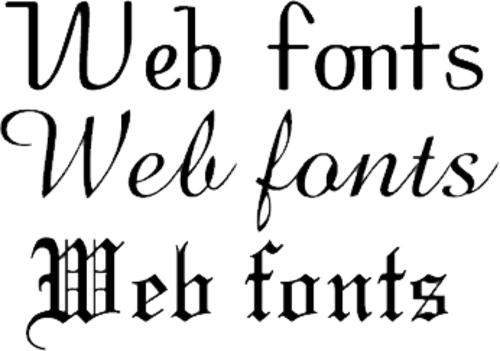
ウェブ タイポグラフィは、一般的なタイポグラフィと同様に、ページのデザイン、つまりレイアウトと書体の選択です。従来の印刷ベースのタイポグラフィ (ページは一度タイプセットされると固定されます) とは異なり、ワールド ワイド ウェブでの表示を目的としたページには追加の技術的課題があり、プレゼンテーションを動的に変更できるため、追加の機会があります。初期のウェブ ページ デザインは、技術的な制限により非常に単純でしたが、最新のデザインでは、カスケーディング スタイル シート(CSS)、JavaScript、およびその他のテクニックを使用して、タイポグラファーとクライアントのビジョンを実現します。
HTMLが最初に作成されたとき、書体とスタイルは各Web ブラウザの設定によってのみ制御されていました。Netscape が1995 年に 要素を導入しfont、その後 HTML 3.2 仕様で標準化されるまで、個々の Web ページでフォントの表示を制御するメカニズムはありませんでした。ただし、要素で指定されたコンピュータ フォントはfont、ユーザーのコンピュータにインストールされているか、ブラウザのデフォルトのサンセリフフォントや等幅フォントなどのフォールバックフォントが使用される必要がありました。最初の CSS 仕様は 1996 年に公開され、同じ機能を提供しました。
CSS2仕様は1998年にリリースされ、フォントのマッチング、合成、ダウンロードを追加することでフォント選択プロセスの改善を試みました。これらの技術はあまり使用されなかったので、CSS2.1仕様では削除されました。しかし、Internet Explorerは1997年にリリースされたバージョン4.0でフォントダウンロード機能のサポートを追加しました。[1]フォントのダウンロードは後にCSS3フォントモジュールに含まれ、 Safari 3.1、Opera 10、Mozilla Firefox 3.5に実装されました。これにより、Webタイポグラフィへの関心が高まり、フォントダウンロードの使用も増加しました。
CSS1
最初のCSS仕様では、[2]著者は一連のプロパティを通じてフォントの特性を指定しました。
font-familyfont-stylefont-variantfont-weightfont-size
すべてのフォントは名前だけで識別されていました。上記のプロパティ以外に、デザイナーがフォントのスタイルを設定する方法はなく、クライアント システムに存在しないフォントを選択するメカニズムもありませんでした。
ウェブセーフフォント
Web セーフ フォントは、幅広いコンピュータシステムに存在することが合理的に期待できるコンピュータ フォントであり、Webコンテンツの作成者が、コンテンツが選択したフォントで表示される可能性を高めるために使用します。Web サイトの訪問者が指定されたフォントを持っていない場合、ブラウザは、作成者が指定したフォールバック フォントと汎用ファミリに基づいて類似の代替フォントを選択しようとするか、訪問者のオペレーティング システムで定義されている フォントの代替を使用します。
Microsoft の Web 向けコアフォント
すべての Web ユーザーが基本的なフォント セットを利用できるようにするために、Microsoft は1996 年にCore fonts for the Webイニシアチブを開始しました(2002 年に終了)。リリースされたフォントには、 Arial、Courier New、Times New Roman、Comic Sans、Impact、Georgia、Trebuchet、Webdings、Verdanaなどがあります。EULAでは、これらのフォントは自由に配布できるものの、使用権が一部制限されていました。これらのフォントは普及率が高いため、Web デザイナーにとって欠かせないものとなっています。ただし、ほとんどのLinux ディストリビューションには、これらのフォントがデフォルトで含まれていません。
CSS2は、フォント合成、フォントマッチングの改善、リモートフォントのダウンロード機能を追加することで、Web開発者が利用できるツールを増やそうとしました。[3]
CSS2フォントプロパティの一部はCSS2.1から削除され、後にCSS3に含まれました。[4] [5]
フォールバックフォント
CSS仕様では、複数のフォントをフォールバックフォントとしてリストすることができます。[6] CSSでは、font-familyプロパティは次のように使用するフォントフェイスのコンマ区切りのリストを受け入れます。
フォントファミリ: "Nimbus Sans L" 、Helvetica 、Arial 、sans-serif ;
最初に指定されたフォントが優先フォントです。このフォントが使用できない場合、Web ブラウザはリスト内の次のフォントの使用を試みます。指定されたフォントが見つからない場合、ブラウザはデフォルトのフォントを表示します。ブラウザが指定されたフォントに存在しない文字を表示しようとした場合も、同じプロセスが文字ごとに実行されます。
汎用フォントファミリー
ウェブデザイナーがウェブページ上のフォントの外観をある程度制御できるように、指定されたフォントが利用できない場合でも、CSS 仕様ではいくつかの汎用フォント ファミリの使用が許可されています。これらのファミリは、フォントを一般的な外観に基づいていくつかのカテゴリに分割するように設計されています。これらは通常、作成者が指定したフォントが利用できない場合の最後の手段として、一連のフォールバック フォントの最後に指定されます。数年間、汎用ファミリは 5 つありました。[6]
- 文字に装飾的なマークやセリフがないフォント。これらのフォントは画面上で読みやすいとよく考えられています。[7]
- 文字に装飾的なマークやセリフがあるフォント。これらのフォントは伝統的に印刷書籍で使用されています。
- すべての文字の幅が等しいフォント。
- 筆記体に似たフォント。これらのフォントは装飾的な外観を持ちますが、小さいサイズでは読みにくいため、通常は控えめに使用されます。
ファンタジー
- 記号やその他の装飾プロパティを含みながらも、指定された文字を表すフォント。
CSS フォントのワーキングドラフト 4 (ブラウザのサポートが少ない)
2024年2月現在[アップデート]、W3CのCSSワーキンググループは、システムがタグを使用してデフォルトのフォントを指定することを提案しています。[8]同日現在、これらはまだ広くサポートされていません。[9]ui
- システムUI
- 特定のシステムのデフォルト フォント: このオプションの目的は、Web コンテンツをネイティブ OS のルック アンド フィールと統合できるようにすることです。
- uiセリフ
- 特定のシステムにおけるセリフ体のデフォルトフォント
- サンセリフ
- 特定のシステム上のサンセリフ スタイルのデフォルト フォント
- ui-モノスペース
- 特定のシステムにおける等幅フォントのデフォルトフォント
- ui-丸め
- 丸みを帯びたスタイルの特定のシステムのデフォルトフォント
- 絵文字
- 絵文字を使ったフォント
- 数学
- 複雑な数式や表現用のフォント。
- Fangsong (中国語:仿宋体)
- セリフ体の宋体と草書体の楷書体の中間に位置する中国語の書体。このスタイルは、政府文書によく使用されます。
ウェブフォント
歴史
リモートフォントを参照して自動的にダウンロードする技術は、この構造を導入したCSS2仕様で初めて規定されました。当時、Webからフォントファイルを取得することは、特定のWebページのみで使用することを意図したフォントもダウンロードしてインストールすることができ、フォントライセンスに違反する可能性があるため、物議を醸していました。[10]@font-face
マイクロソフトは1997年に初めてInternet Explorer 4でダウンロード可能なEOTフォントのサポートを追加しました。著者は各ページのサブセットフォントファイルを作成するために独自のWEFTツールを使用する必要がありました。EOTはWebフォントが機能することを示し、このフォーマットは一般的なオペレーティングシステムでサポートされていない書記体系で使用されました。しかし、このフォーマットは広く受け入れられることはなく、最終的にはW3Cによって拒否されました。[11]
2006年、Håkon Wium LieはEOTの使用に反対し、むしろウェブブラウザで一般的に使用されているフォント形式をサポートするよう求めるキャンペーンを開始しました。[12] [13] [14]それ以来、一般的に使用されているTrueTypeおよびOpenTypeフォント形式のサポートは、 Safari 3.1、Opera 10、Mozilla Firefox 3.5、Internet Explorer 9に実装されています。
2010年に、 TrueTypeフォントとOpenTypeフォントのWOFF圧縮方式がMozilla Foundation、Opera Software、MicrosoftによってW3Cに提出され、それ以来ブラウザがサポートを追加しました。[15] [16] [17]
Google Fontsは、オープンソースライセンスの下でウェブフォントを提供するために2010年に開始されました。2016年までに、800を超えるウェブフォントファミリーが利用可能になりました。[18]
ウェブフォントはウェブデザイナーにとって重要なツールとなり、2016年現在では大多数のサイトがウェブフォントを使用しています。[19]
ファイル形式
特定の CSS埋め込み技術[20]を使用することで、IE4+、Firefox 3.5+、Safari 3.1+、Opera 10+、Chrome 4.0+ で動作するようにフォントを埋め込むことができます。これにより、大多数の Web ユーザーがこの機能を利用できるようになります。商用フォント ファウンドリーの中には、自社のフォントの再配布に反対するところもあります。たとえば、Hoefler & Frere-Jones は、「デザイナーがオンラインで高品質フォントを安全かつ確実に使用できる、より表現力豊かな Web の出現を熱心にサポートする」一方で、フォントの現在の配信はファウンドリーによって「違法な配信」と見なされ、許可されていないと述べています。[21]代わりに、Hoefler & Co. はクラウドを基盤とした独自のフォント配信システムを提供しています。他の多くの商用フォント製造業者は、フォントの再配布に対処するために、ウェブフォントライセンスと呼ばれる特定のライセンスを提供しています。このライセンスでは、ウェブ上のコンテンツを表示するためにフォントソフトウェアを使用することが許可されます。これは、通常、基本的なデスクトップライセンスでは禁止されている使用です。当然、これはフリーライセンスのフォントや製造業者に干渉するものではありません。[m 1]@font-face@font-face
トゥルードック
TrueDoc はウェブフォント仕様というわけではないが、埋め込みフォントの最初の標準だった。 1994年にフォントファウンドリーのBitstreamによって開発され、1996年にNetscape Navigator 4 でネイティブサポートされた。オープンソースライセンスの制約により、Netscape は Bitstream のソースコードを公開できなかったため、Netscape Navigator 6 のリリース時にこの技術のネイティブサポートは終了した。Internet Explorerに TrueDoc のサポートを追加するためのActiveXプラグインは利用可能だったが、この技術は、バージョン 4.0 以降 Internet Explorer ブラウザーでネイティブサポートされているMicrosoftのEmbedded OpenTypeフォントと競合しなければならなかった。 [22]もう 1 つの障害は、TrueDoc 形式のウェブフォントを作成するためのオープンソースまたは無料ツールがなかったことである。一方、Microsoft は、自社の形式でウェブフォントを作成するための無料のWeb Embedding Fonts Tool を提供していた。